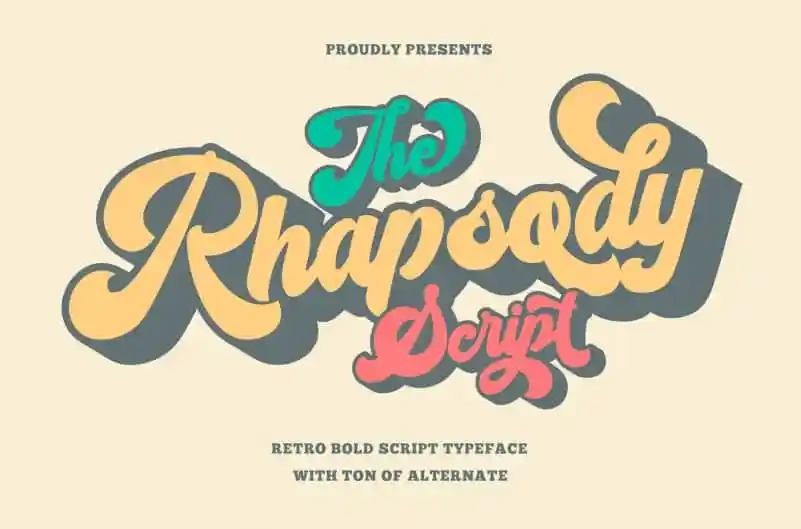
Rhapsody – Bold Script Typeface – Download Grátis
Rhapsody é uma fonte de script bold inspirada nos designs vintage dos anos 70. Esta fonte leva você para um tempo retrô instantaneamente, perfeita para usar em logotipos de design vintage, camisetas vintage, selinhos retro, identidade visual de citações, embalagens e até mesmo marcas de slogan nostálgicos. Seja qual seja o seu projeto que exige um toque de nostalgia, Rhapsody pode ser a escolha certa. Sua linhas leves e elegantes combinam perfeitamente com textos em grande tamanho para criações memoráveis de design. Sem dúvida, esta fonte irá tornar seus projetos únicos e autênticos, remetendo ao melhor da década de 70. Seja você um designer ou uma marca que busca criar algo vintage, Rhapsody é a escolha perfeita para você.